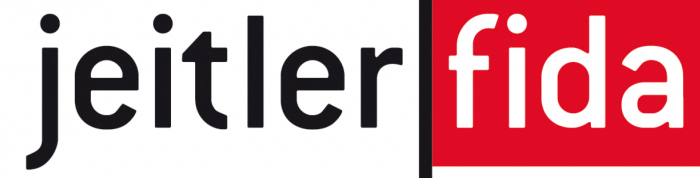
DIN-ähnliche mit hässlichem »t«
verehrte kollegas, erbitte heute eure mithilfe bei der suche nach dieser schrift. erkennt das wer? geht stark in richtung DIN, ist es aber nicht. vermute eher einen freefont. (weil t und a ziemlich ungelenk aussehen)
das ist der schriftzug eines bestehenden unternehmens, den ich nachbauen muss. auf der website gibt’s den font nicht als webfont, die buttons sind als bilder eingebaut. die downloadbaren pdfs haben das logo allesamt als bild eingebaut. dort fragen erscheint derzeit nicht klug.
mir kommt die schrift eh bekannt vor, vielleicht riecht der bertel gleich aus welchem stall das vieh kommt (oder schwalbenkönig kommt aus dem winterschlaf?)